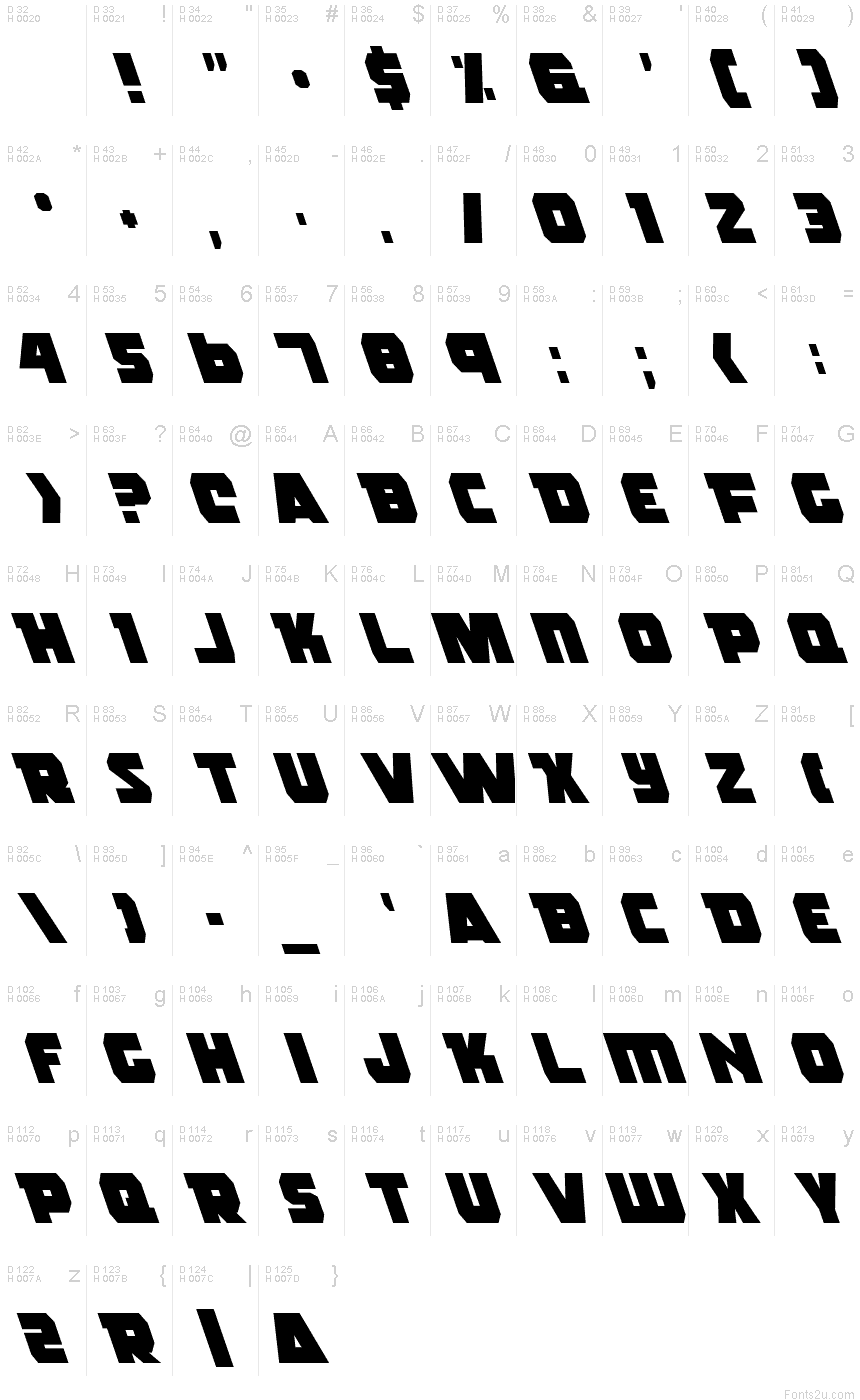
Rogue Hero Left od Iconian Fonts to darmowy, kanciasty font display w stylu techno o ostrym, futurystycznym charakterze. Wielkie litery sprawiają wrażenie wykutych z ciężkich, geometrycznych bloków, a wyraziste cięcia ukośne i blokowe wcięcia nadają im szybki, opancerzony wygląd, kojarzący się bardziej z grami wideo niż z gładką elegancją.
Dzięki temu ten darmowy font świetnie sprawdzi się na plakatach sci-fi, w brandingu esports, tytułach gier, na okładkach komiksów oraz w wyrazistych projektach logo. Idealnie pasuje też do krótkich nagłówków i monogramów, gdzie powtarzalne kliny i rozdzielone pociągnięcia nadają nawet krótkim słowom napięty, mechaniczny rytm.